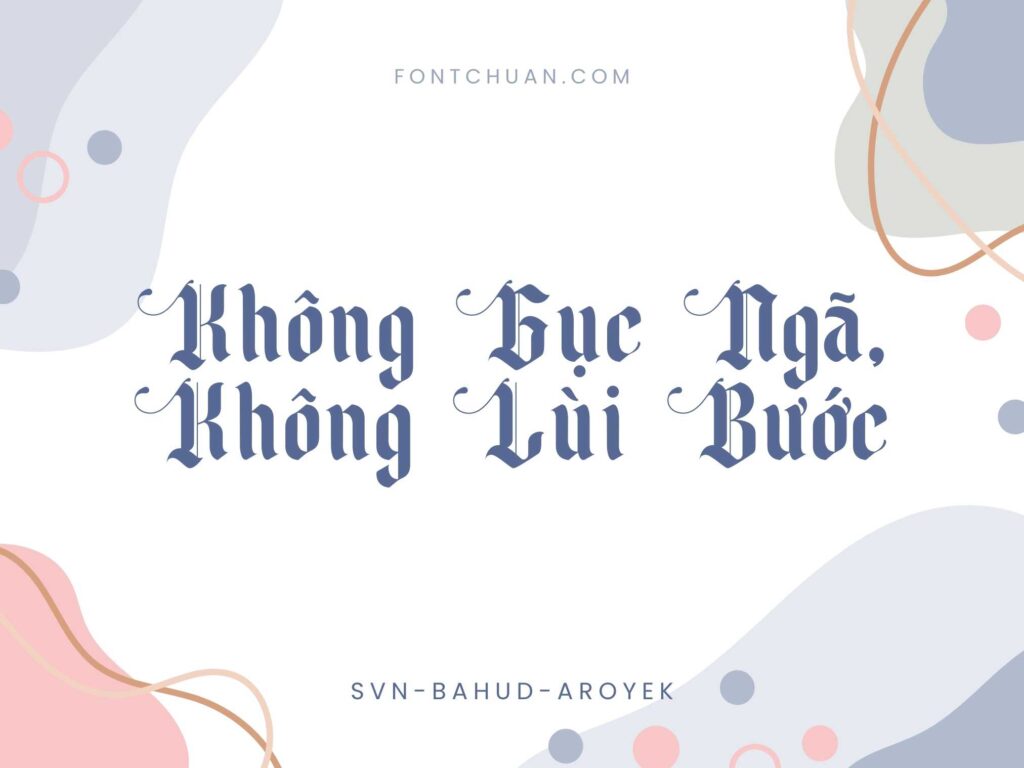
Font SVN Bahud Aroyek Việt Hóa
Tác giả Font: Gilang Maulana
Bahud Aroyek là một font chữ hiển thị độc đáo, được thiết kế bởi Maulana Creative. Font này mang phong cách cổ điển với sự kết hợp giữa kiểu chữ Blackletter và các yếu tố trang trí hiện đại, tạo nên sự mạnh mẽ và ấn tượng cho các thiết kế. Bahud Aroyek đã được Việt hóa để hỗ trợ tiếng Việt bởi Styleno.1 Fonts, đồng thời hỗ trợ nhiều ngôn ngữ khác, giúp mở rộng phạm vi sử dụng trên toàn cầu. Font này được thành viên của Font Chuẩn sưu tầm và chia sẻ, đáp ứng nhu cầu của bạn đọc và ứng dụng thực tế vào các dự án thiết kế.
Đặc điểm thiết kế của Bahud Aroyek bao gồm các đường nét đậm, góc cạnh và chi tiết trang trí phức tạp, tạo cảm giác cổ điển và quyền lực. Font này phù hợp cho các ứng dụng như thiết kế logo, tiêu đề, bìa sách, poster và các dự án cần sự nổi bật. Các ngành nghề phù hợp bao gồm quảng cáo, nghệ thuật và giải trí.